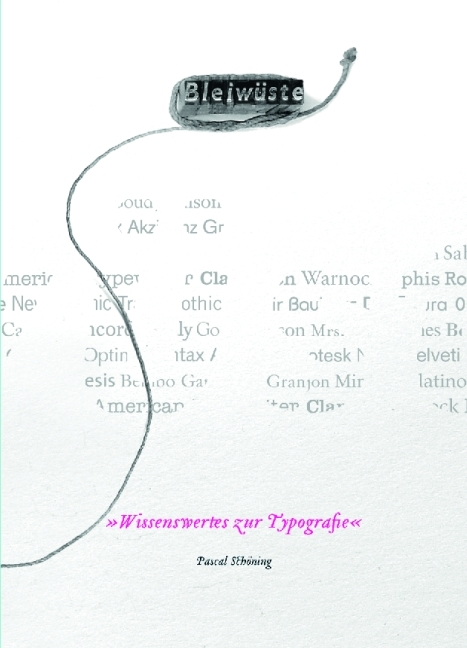
Bleiwüste. Wissenswertes zur Typografie
Die Bleiwüste ist ein nützliches Handbuch, das Interessierte, Einsteiger und Studenten mit auf eine typografi sche Reise nimmt. In drei reich bebilderten Teilen werden verschiedene Aspekte der Typografie behandelt. Leichten Zugang zu den Informationen bietet das Register. Der erste Teil stellt fünfzig der bedeutendsten Schriftarten - von Bodoni bis Thesis - vor und erklärt anhand der spezifischen Merkmale ihrer Buchstaben die Unterschiede, aber auch das Einsatzgebiet und die Anwendbarkeit der Schriften. Jede Schrift wird mit einem Anwendungsbeispiel illustriert und bietet zudem biografische Informationen zum Schriftschneider oder Schriftgestalter. Der zweite Teil der Bleiwüste ist eine Hommage an die Bleisatzzeit. Von Affenstall bis Zwiebelfischwird humorvoll auf die Bedeutung und Herkunft dieser Wörter eingegangen. Praktisch und unverzichtbar für Typografen zeigt sich der dritte Teil dieses Buches: Tipps und Tricks für Gestalter, die auf der Suche nach der richtigen Tastenkombination für Sonderzeichen, einer Terminologie der Schrift, den richtige Korrekturzeichen oder Papier- u ca. 256 Seiten, reich illustriert nd Bogenformaten sind.